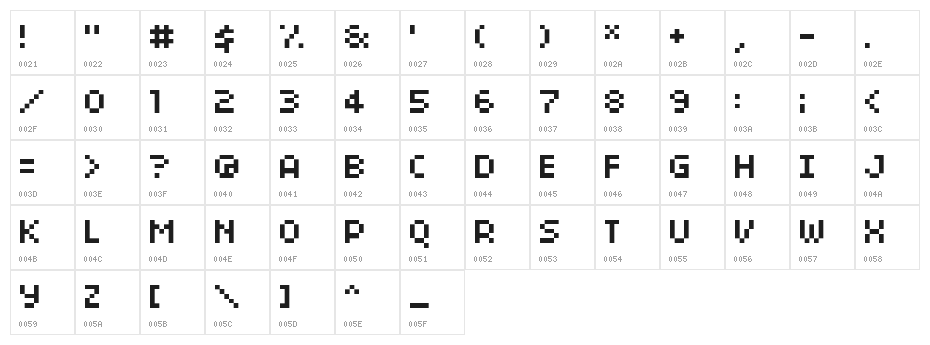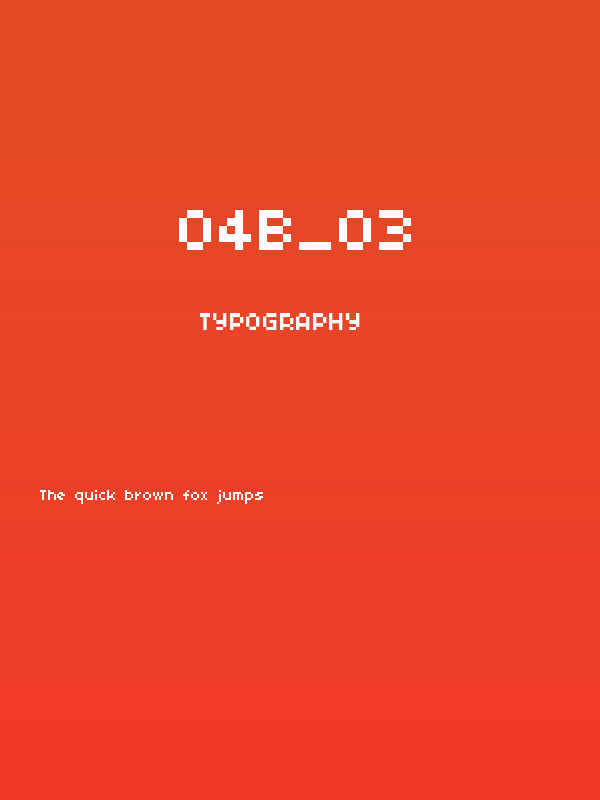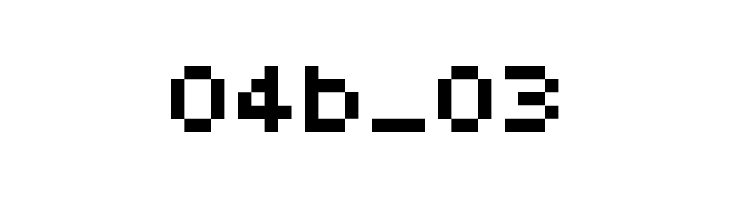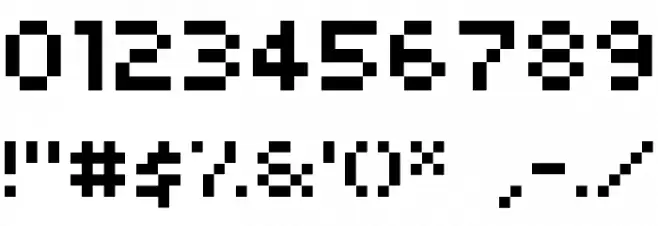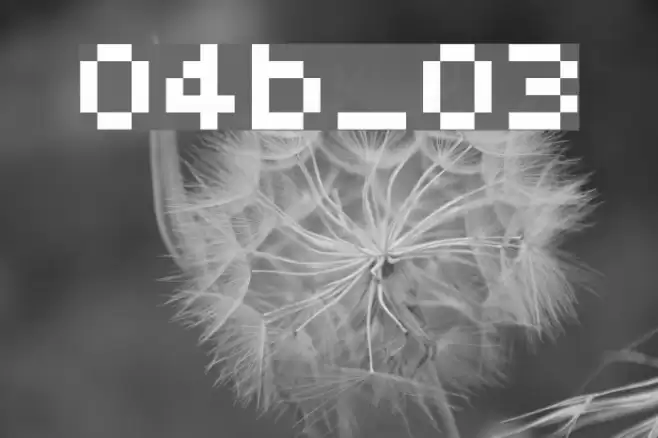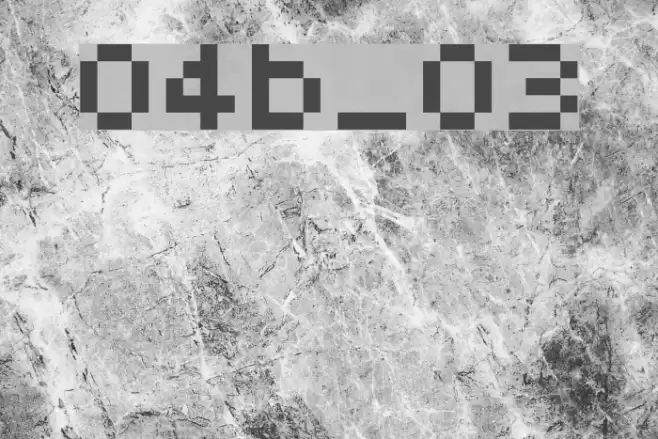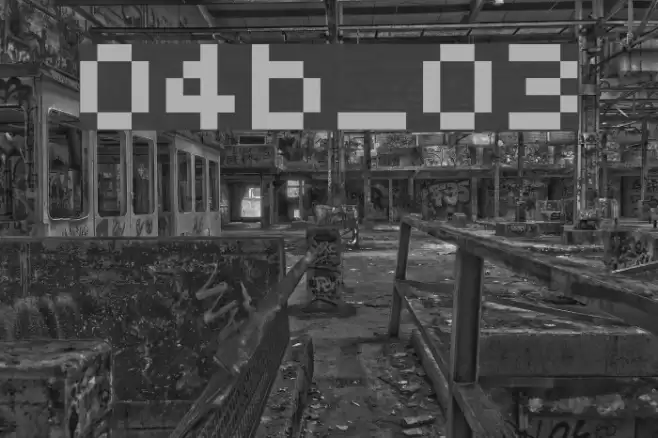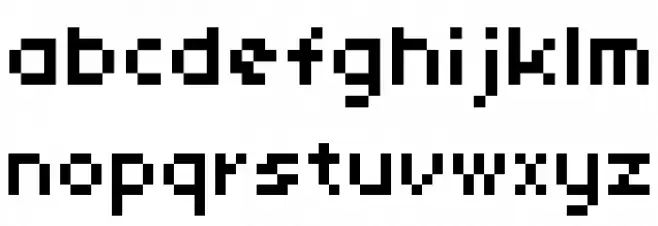
04b_03 Font
| Estilo general | Retro, Digital |
| Caso de uso | Headlines, Logos, Digital Art |
| Proyectos propuestos | Ideal for retro video game designs, digital art projects, tech-themed posters, and any creative work that seeks to capture a nostalgic digital era. |